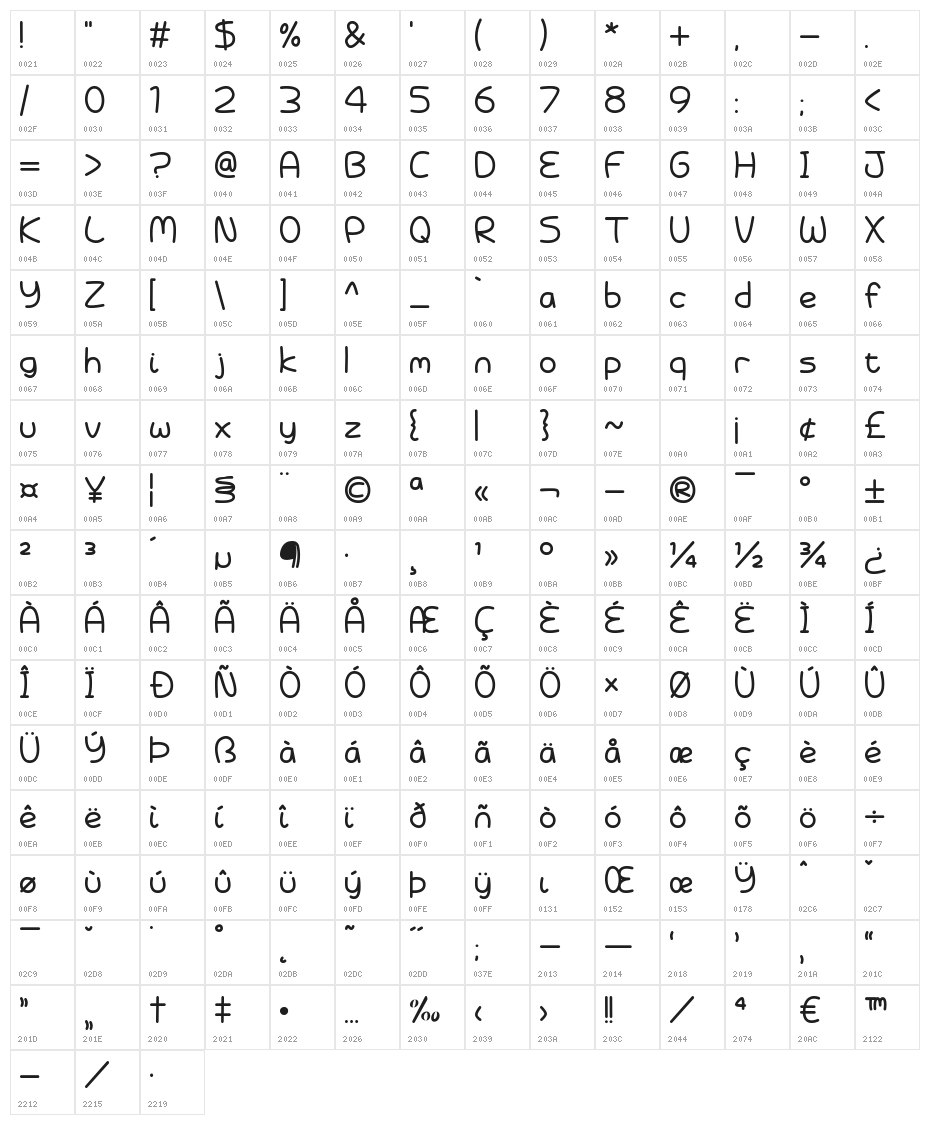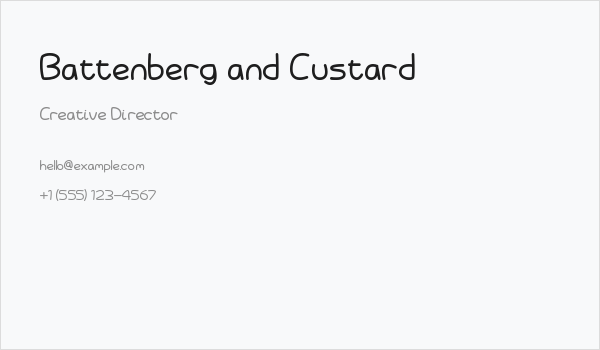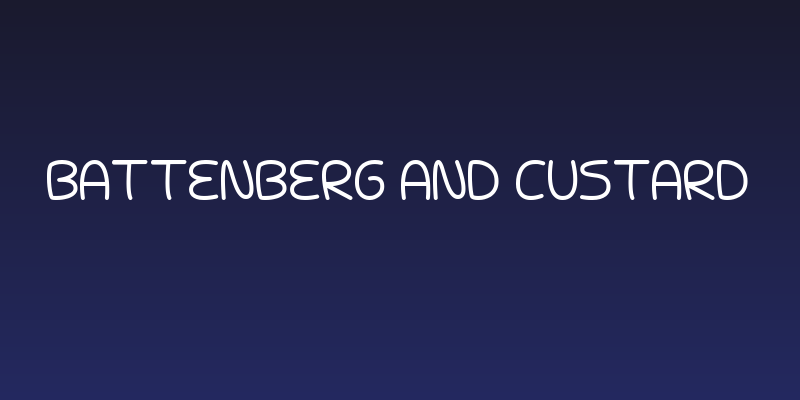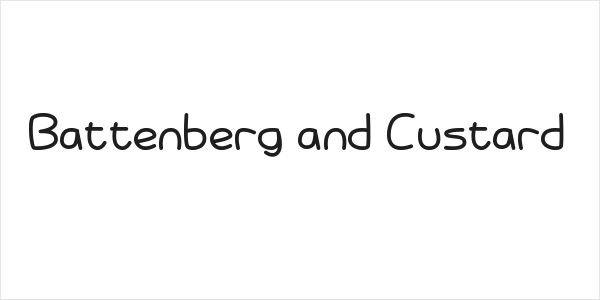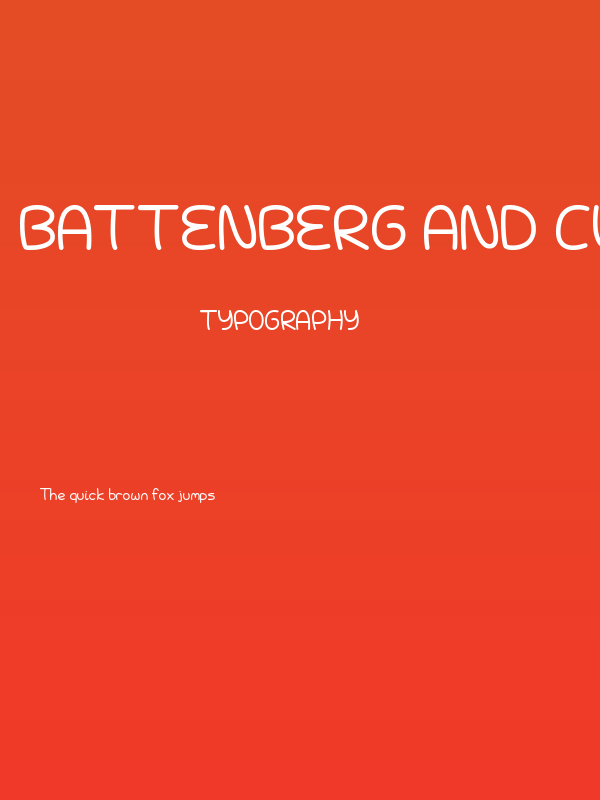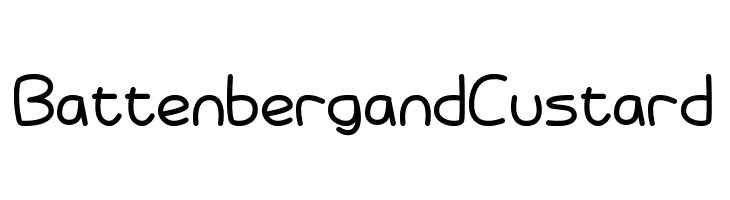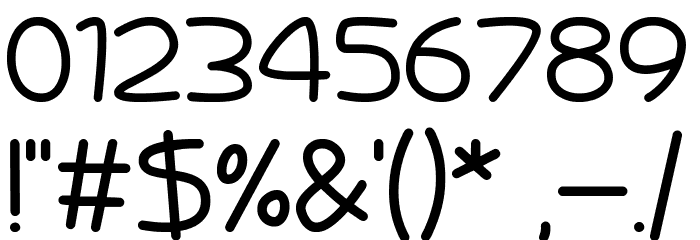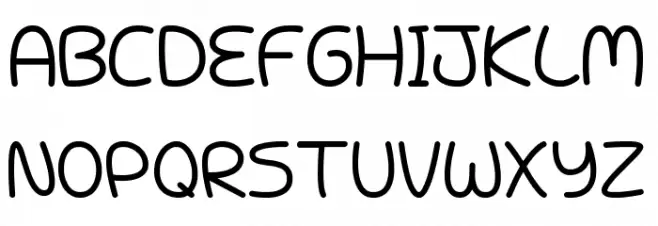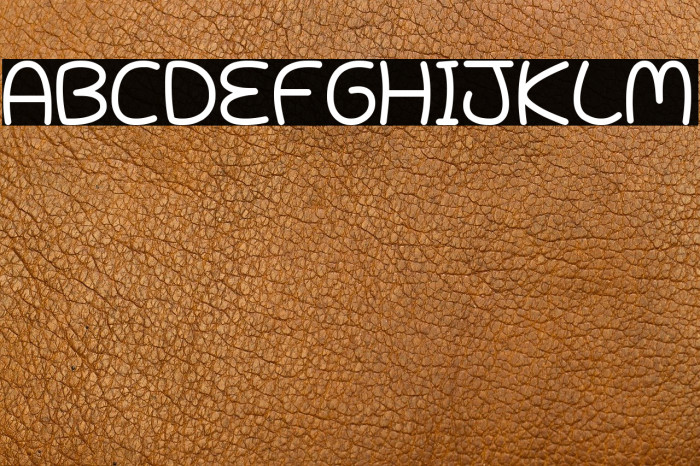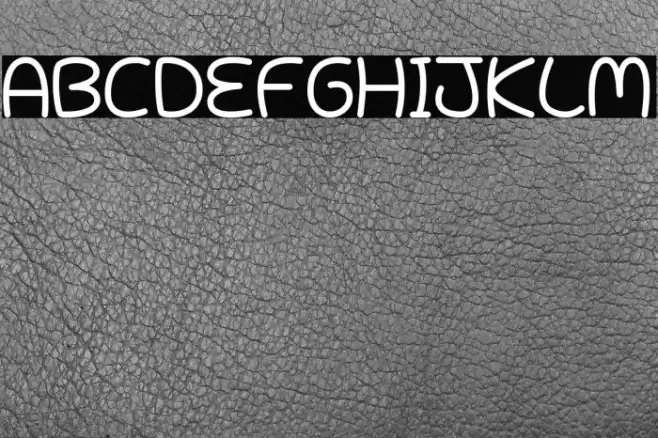
Battenberg and Custard Font
| Stile generale | Casual |
| Caso d'uso | Headlines, Logos, Informal Text |
| Progetti proposti | Ideal for children's books, playful branding, casual invitations, and educational materials. |
| Autore | Fonts by Pablo Impallari |